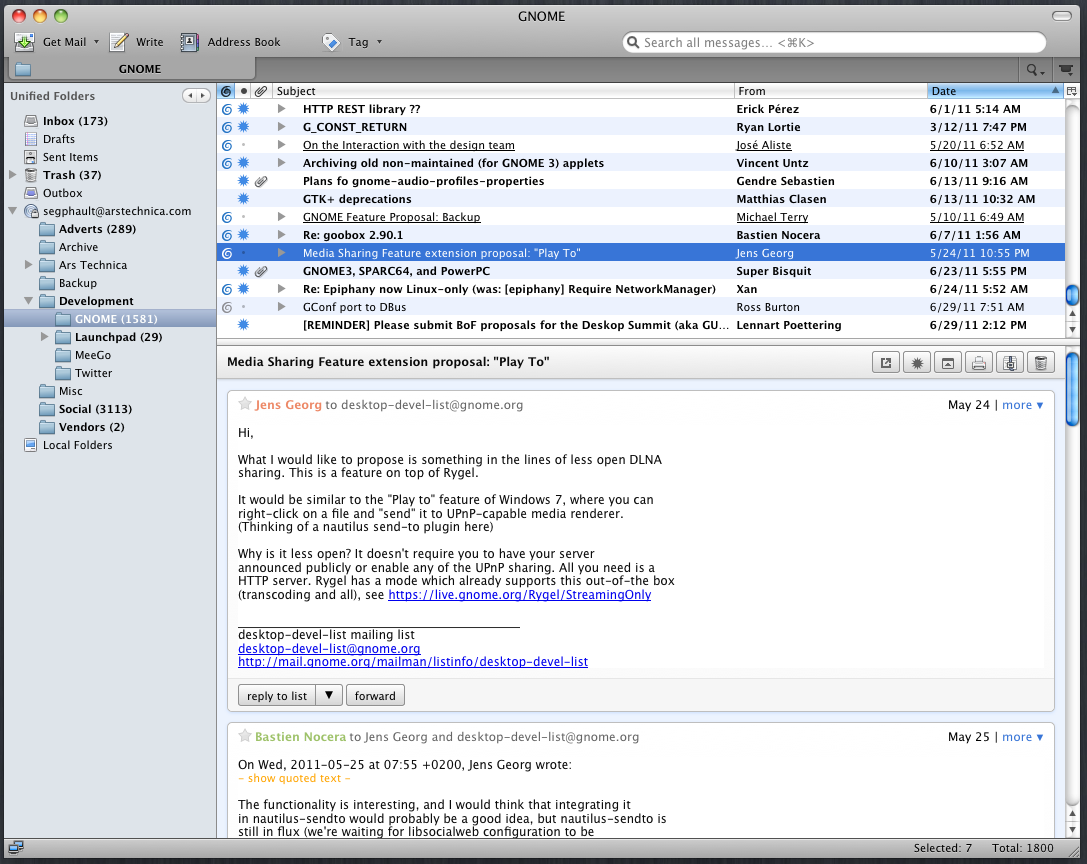
Daher wäre es m.E. am allerwichtigsten, darauf zu achten, dass es in einem Format gespeichert ist, dass jederzeit auch ohne besondere Software wieder gelesen und editiert werden kann. Enthält der Text keine wichtigen Formatierungen, am besten plain text; ansonsten XML. Keinesfalls DOC! Selbst RTF würde ich vermeiden.
Also eine Datenbank verwenden und für die Zukunftssicherheit jeden Tag alles als reinen Text rausexportieren ...
Hm das ganze in Plain-Text, oder TeX oder Markdown in ein Versionsverwaltungssystem,  wie z. B. ein Git-Repo stecken, so hätte man übersicht und könnte sich das ganze auch ordnen.
Das hängt sehr davon ab, wie das Tagebuch im Moment formatiert ist. Nehmen wir mal an, dass Einträge einfach durch Leerzeilen voneinander getrennt sind, innerhalb von Einträgen aber keine Leerzeilen vorkommen, kann es für einen erfahrenen Skriptsprachenbenutzer eine Sache von Sekunden sein, die Reihenfolge der Einträge umzukehren.
Ich würde generell einen anderen Schwerpunkt setzen. Was ist denn an einem Tagebuch überhaupt das wichtigste? Ich denke: dass es auch in etlichen Jahren noch gelesen werden kann. Daher wäre es m.E. am allerwichtigsten, darauf zu achten, dass es in einem Format gespeichert ist, dass jederzeit auch ohne besondere Software wieder gelesen und editiert werden kann. Enthält der Text keine wichtigen Formatierungen, am besten plain text; ansonsten XML. Keinesfalls DOC! Selbst RTF würde ich vermeiden.
vollkommen richtig torsten, deswegen verwende ich auch seit über 10 Jahren plain text als tagebuch. das projekt Gutenberg verwendet aus demselben Grund auch reinen text. Die Gliederung schaut so aus:
ÜBERSCHRIFT DES TAGES (2013-05-24)
1 absatz
textkörper, ein längerer Text wird natürlcih durch Absätze getrennt.
2 Absätze zu nächstem Tagebucheintrag
NEUER TAGEBUCHEINTRAG (2013-05-25)
Eine Datenbank ist auch meiner Meinung nach das Mittel der Wahl, daraus kannst Du dann verschiedene Formate und Reihenfolgen ausgeben lassen. Eine Möglichkeit ist Openoffice/Libreoffice Base. Ich habe aber keine Erfahrung mit lokalen Datenbanken und kann deshalb auch keine empfehlen.
Kathrin: Du machst es wirklich falsch! Es ist völlig unnötig, immer den ganzen Nachrichtenverlauf mitzuschicken, denn ein ordentliches Netzpostprogramm kann die Nachrichten und zugehörigen Antworten untereinander anzeigen:
Wenn sich dann Nachrichten mit zig angehängten Vollzitaten abwechseln, ist das nur noch sehr schwierig zu lesen, weshalb TOFU äußerst nervig ist. Bedenke außerdem, daß es unsinnig die Datennetze belastet, immer wieder die gleichen Texte hin- und herzuschicken, und unnötig Speicherplatz belegt, immer wieder die gleichen Texte zu speichern. Stelle also besser Dein Programm vernünftig ein — oder steige auf ein ordentliches Programm um, z. B. Postbox. :-)
Und wenn ich ein digitales Tagebuch schreiben würde, dann würde ich dies jedenfalls nicht in einer einzigen Textdatei, die ich dann, immer größer werdend, ja immer komplett laden müsste, schreiben, sondern jeden Tag einzeln als Datensatz in einer Datenbank. Dann kann man nämlich direkt jeden beliebigen Tag anspringen, statt sich durch einen endlosen Text hindurch zu wühlen, egal ob das neueste nun oben oder unten steht. Sucht man etwas, steht das ohnehin immer am falschen Ende.
Das ist dann aber ein Problem für jene, die die Benutzung der Fraktur auch für moderne Texte propagieren. Heutzutage gibt es nun einmal jede Menge feststehender Begriffe, die nur in Versalien geschrieben werden – und längst nicht alle sind Fremdwörter oder gehen auf Fremdwörter zurück.
ADAC, TÜV, EDV, CDU, SPD und und und. Wie soll man das in Fraktur setzen?
Gar nicht. auch in alten Büchern der Fraktur-Zeit wurden solche Abkürzungen, genau wie Fremdworte in einer vom Duktus passenden Antiquaschrift in den Frakturtext eingefügt, auch wenn ADAC früher ein Logo aus Fraktur-Buchstaben hatte, da standen die allerdings recht einzeln.